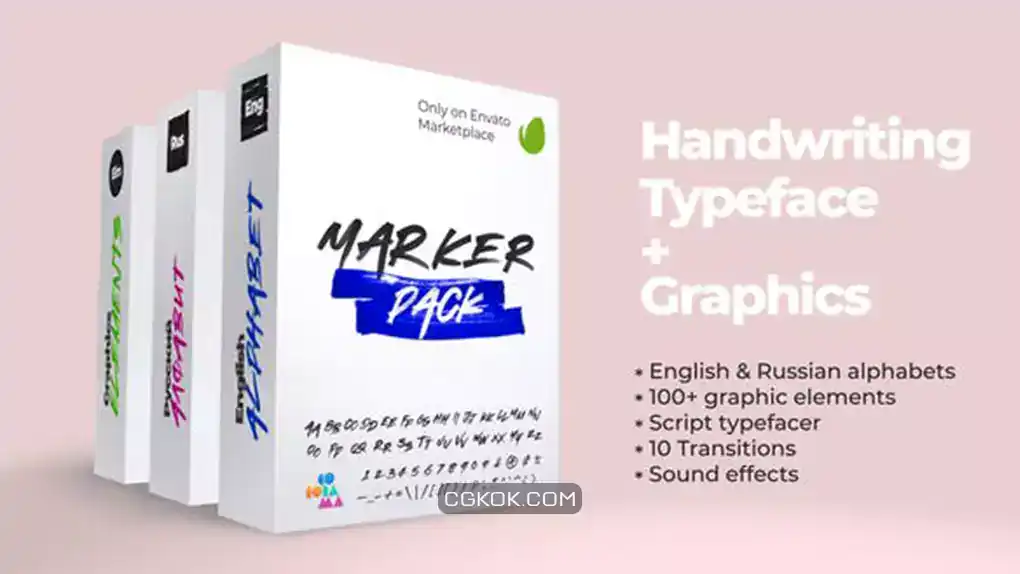
پروژه افترافکت فونت دست نویس متحرک : این پروژه یک قالب ویدیویی آماده انیمیشن فونت به سبک دست ساز با یک اسکریپت Typefacer برای ساخت عناوین متنی متحرک میباشد. این مجموعه شامل بیش از 100 المان گرافیکی، 10 ترانزیشن، الفبای انگلیسی و روسی با حروف بزرگ، کوچک، اعداد و نماد ها میباشد. این محصول قابلیت اجرا و سازگاری کامل با نرم افزار افترافکت CC 2015 و ورژن های بالاتر را دارد. این پروژه دارای رزولوشن 1080 × 1920 است و کار با آن نیاز به پلاگین ندارد.